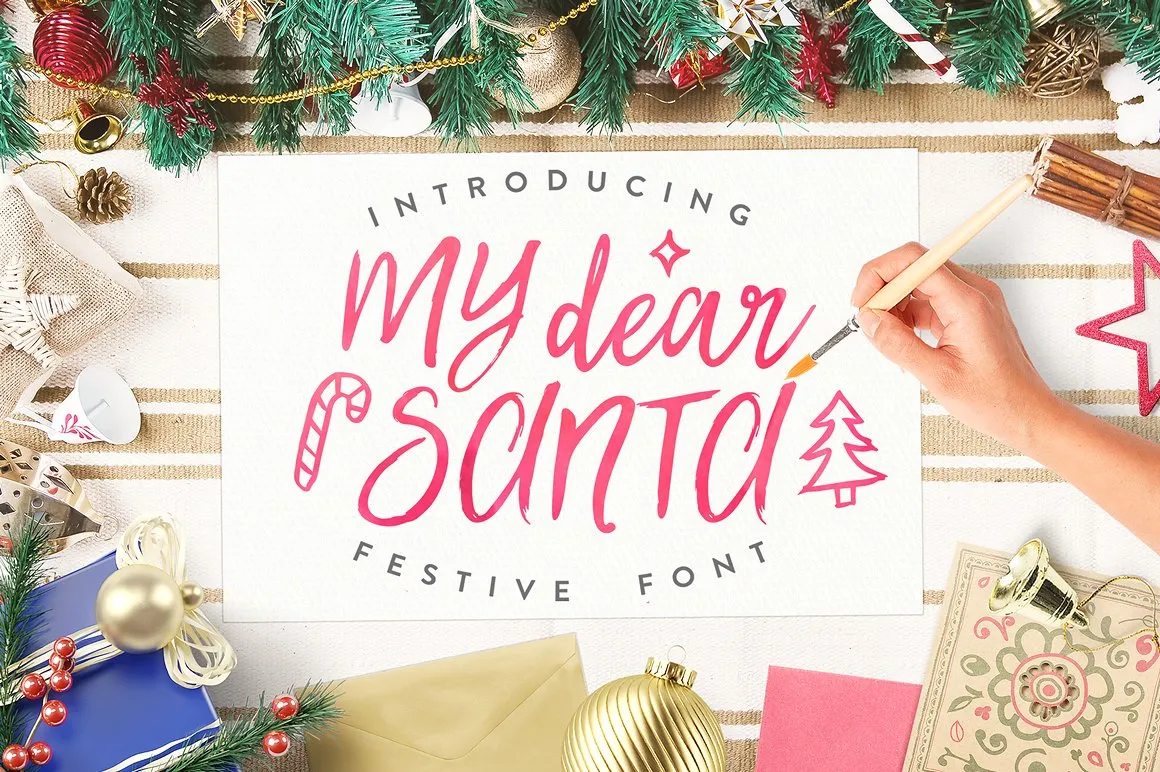
My Dear Santa Script Font
Esta fonte “My Dear Santa Script Font” é perfeita para criar uma atmosfera natalina vibrante. Desenvolvida pelo designer 178-MC, esta fonte brush esculpida é ideal para quem busca uma forma única e criativa de celebrar o espírito de Natal. Se você adora a ideia de escrever cartas pessoais ao Papai Noel ou decorar suas decorações com um toque autêntico do natal, esta fonte será perfeita. “My Dear Santa” captura a essência da festa e permite que você personalize sua experiência de Natal ainda mais. Não perca essa oportunidade única para adquirir uma fonte tão especial. Sempre com um toque criativo e elegante, este é o recurso gráfico ideal para criar lembranças emocionantes durante esta época do ano cheia de magia e celebração.